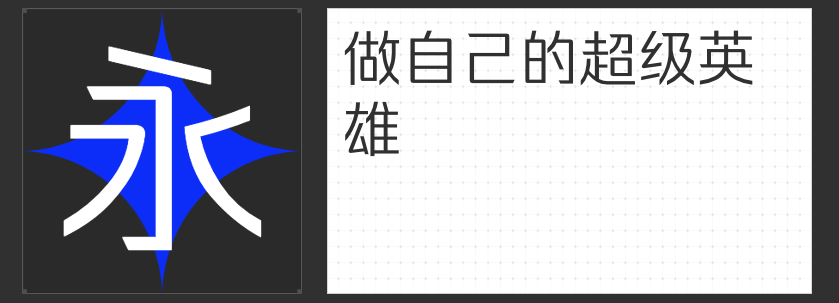
四款精品字库字体推荐:为包装设计注入独特魅力
在包装设计的视觉语言中,字体不仅是信息传递的载体,更是品牌调性与产品气质的直观表达。以下四款各具特色的字库字体,以其独特的设计语言与专业品质,为高端包装设计提供了丰富的创意选择。
一、字恋狂澄空 鸣风
这款以手写感为核心的字体,通过"上松下紧"的动态结构与略低重心,营造出轻盈而不失稳定的视觉韵律。其笔画设计巧妙融合流畅弧线与利落直线,折笔处采用平直切角处理,既保留书写温度又避免视觉锐度。字面率随字形结构自然变化,搭配精心调整的字间距,使标题组合如音符般富有节奏感。特别适合有机食品、文创产品等强调自然与人文关怀的包装设计。
二、励字超级勇士简 常规
作为几何化设计的典范,这款黑体以严谨的骨骼结构承载优雅气质。通过现代笔形处理技术,将传统黑体的机械感转化为柔和舒适的视觉体验。笔画粗细过渡自然,转角处采用微弧设计,在保持专业感的同时注入人文温度。适用于科技产品、高端日化等需要传递可靠性与品质感的包装场景。
三、励字跨界黑简 超级黑
90%的字面率与宽大中宫构建出极具存在感的视觉框架,夸张的粗度设计通过直线与曲线的精妙搭配避免呆板。钩笔画采用微上扬曲线,收笔处根据空间关系灵活斜切,在保证识别性的前提下创造动态平衡。这款字体尤其适合运动品牌、能量饮料等需要突出视觉冲击力的包装标题设计。
四、励字综艺简繁
通过极致的笔画粗度与精心控制的负空间,这款字体创造出充满现代感的块面结构。转角处采用圆润方正的复合处理,既保持横平竖直的秩序感,又赋予字体灵动气质。其艺术性与实用性的高度统一,使其成为美妆、奢侈品等强调设计美学的包装领域的理想选择。
这四款字体均通过专业设计团队反复打磨,在保持商业可用性的同时,为设计师提供了丰富的创意表达空间。无论是追求自然灵动、现代优雅,还是力量冲击、艺术美感,都能找到契合品牌气质的解决方案。